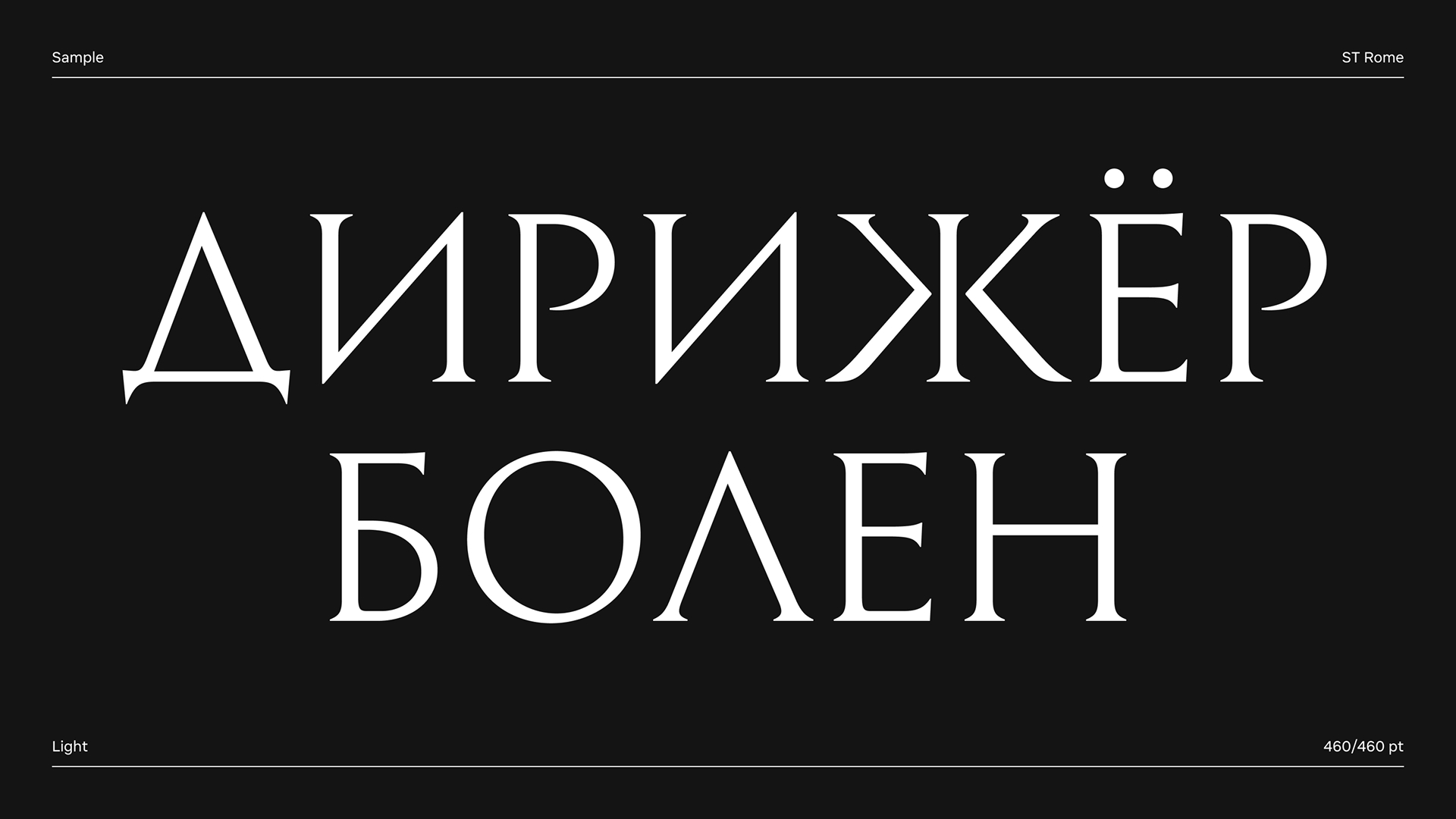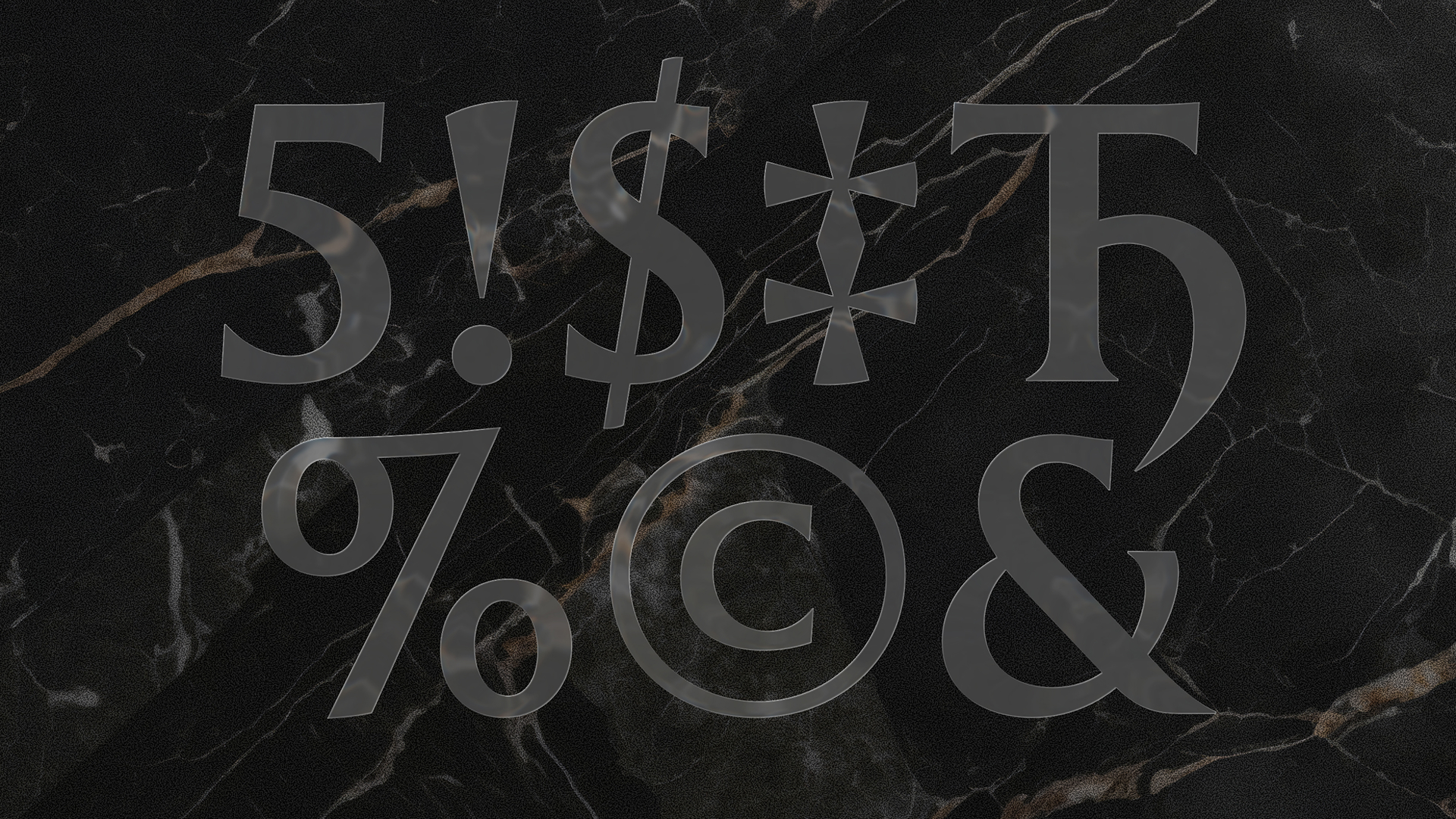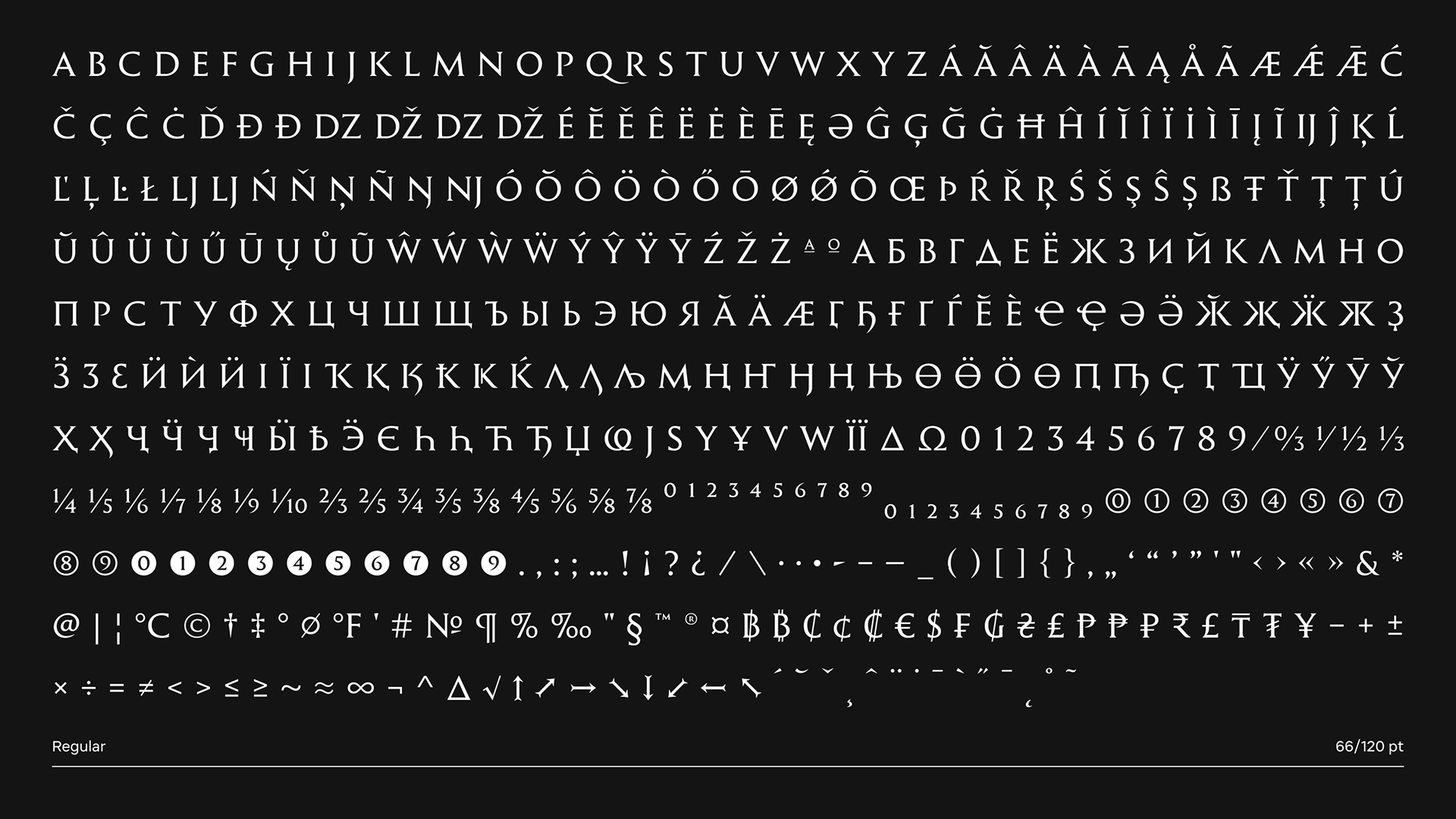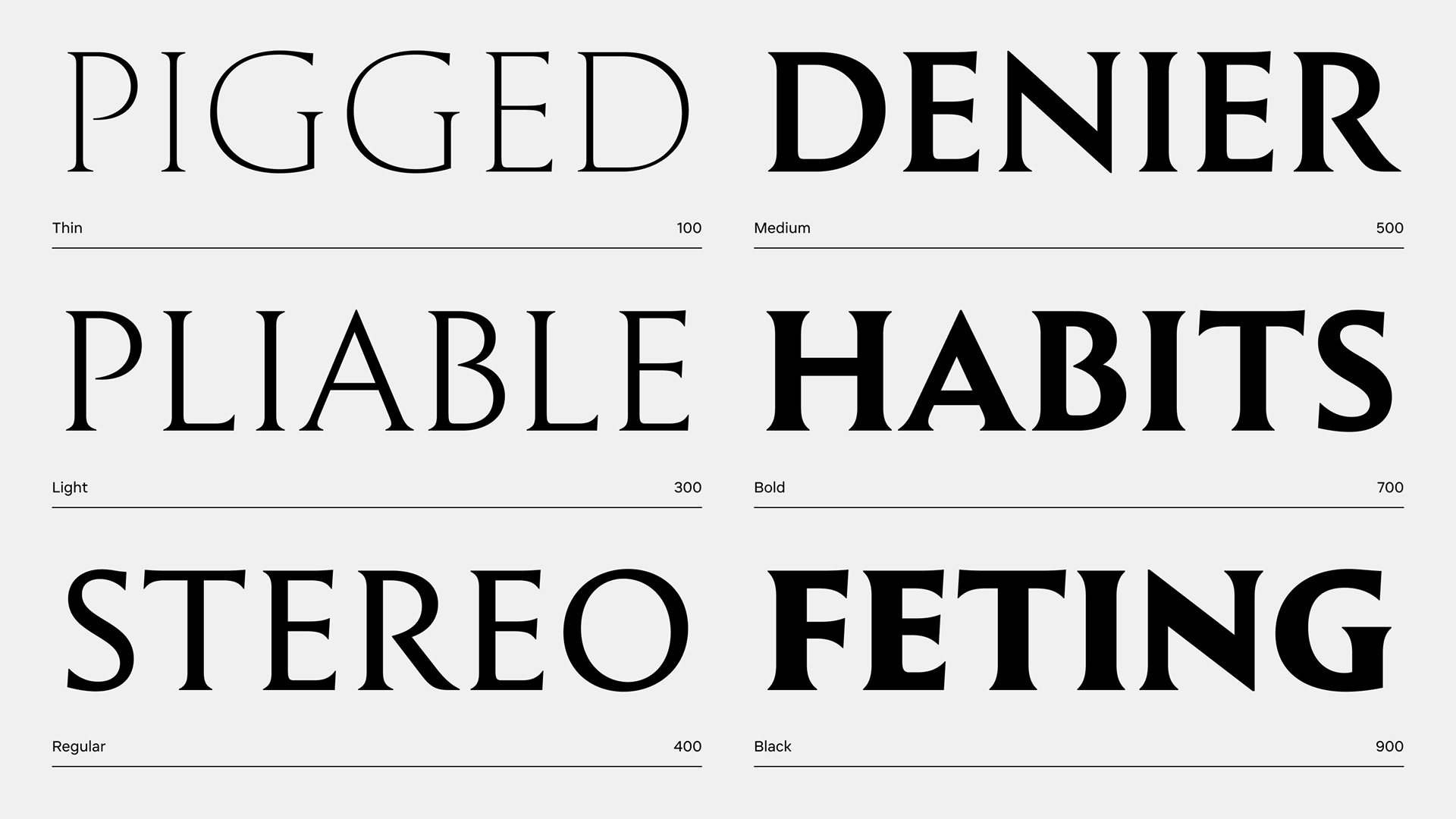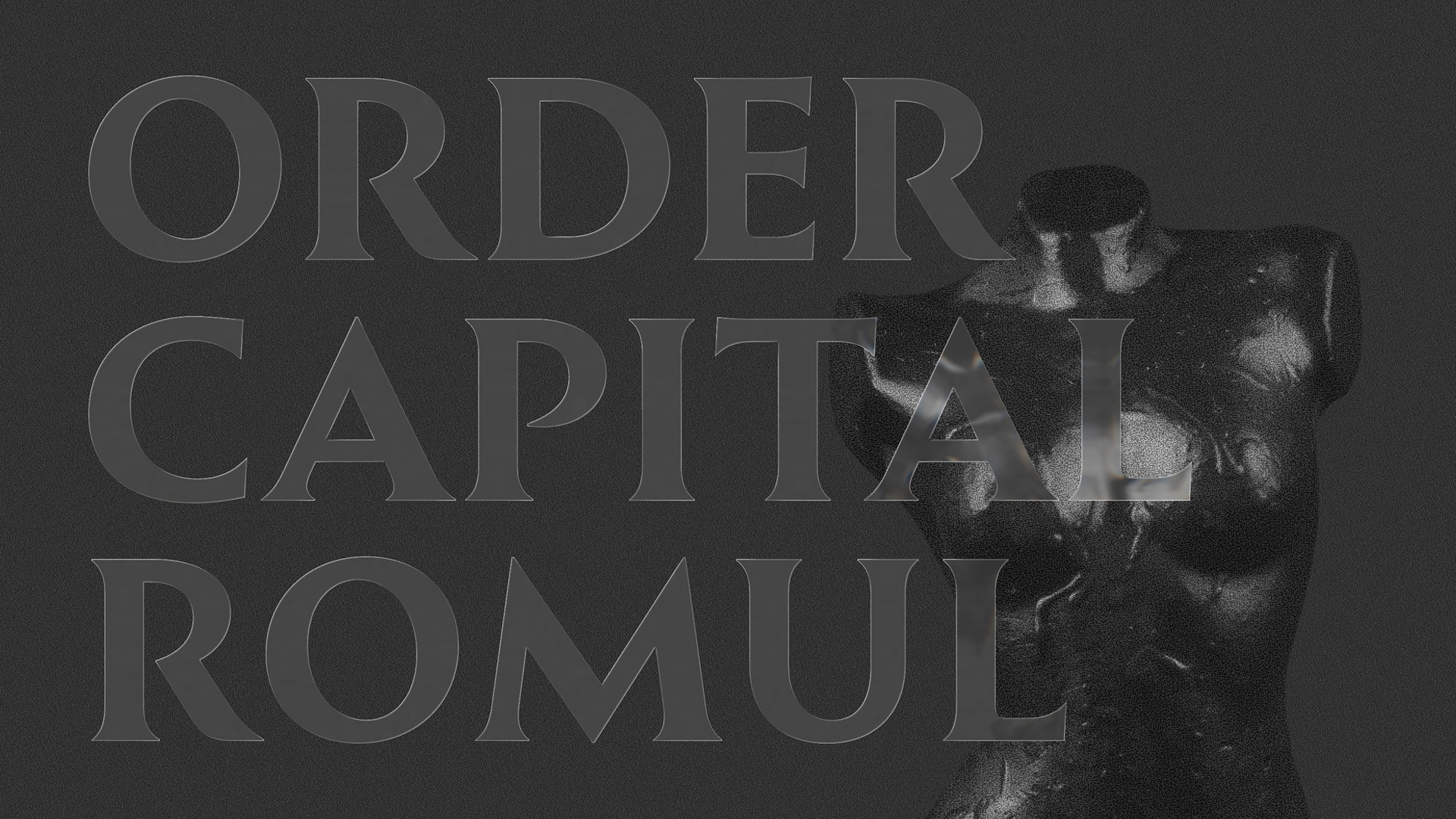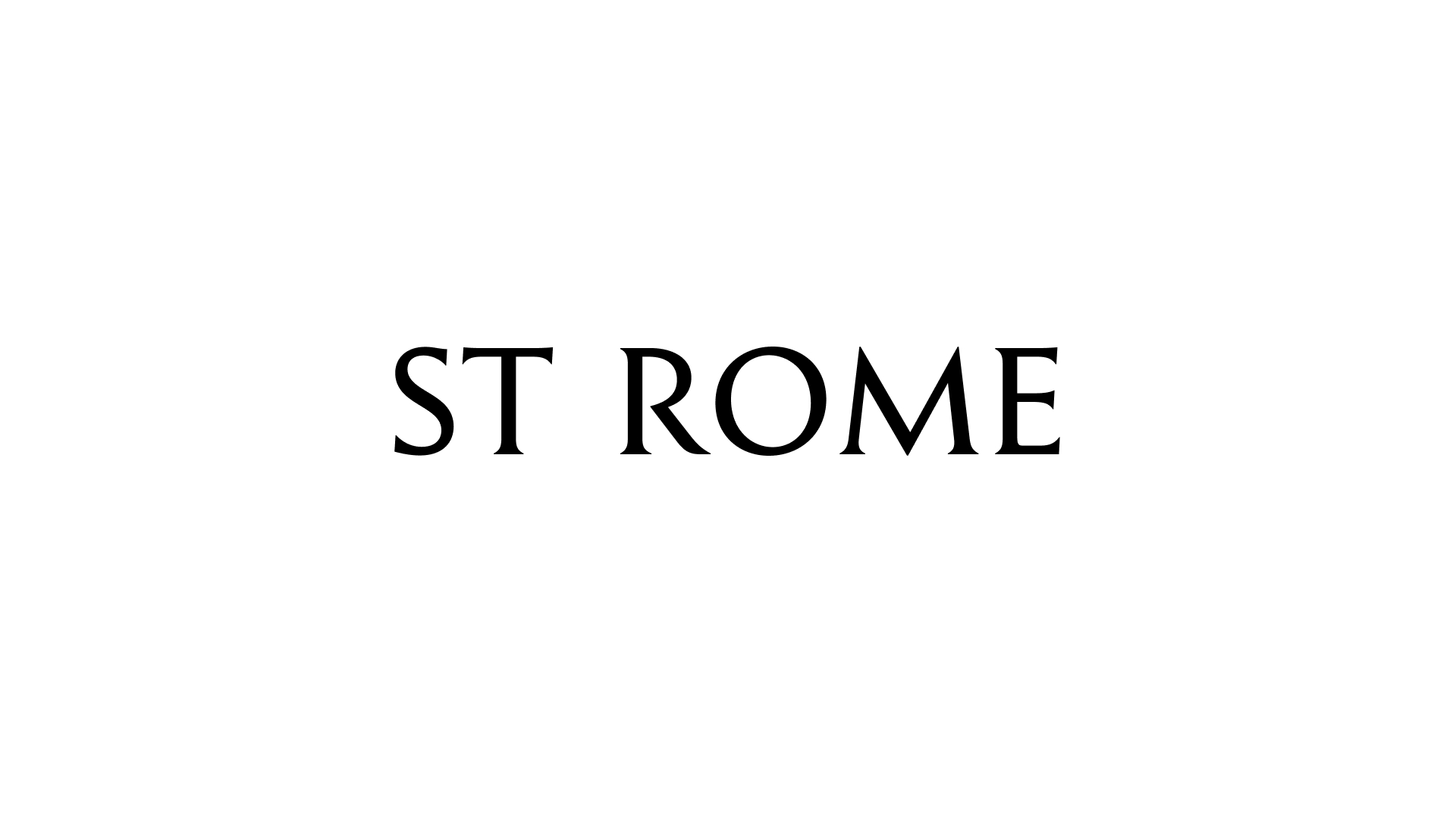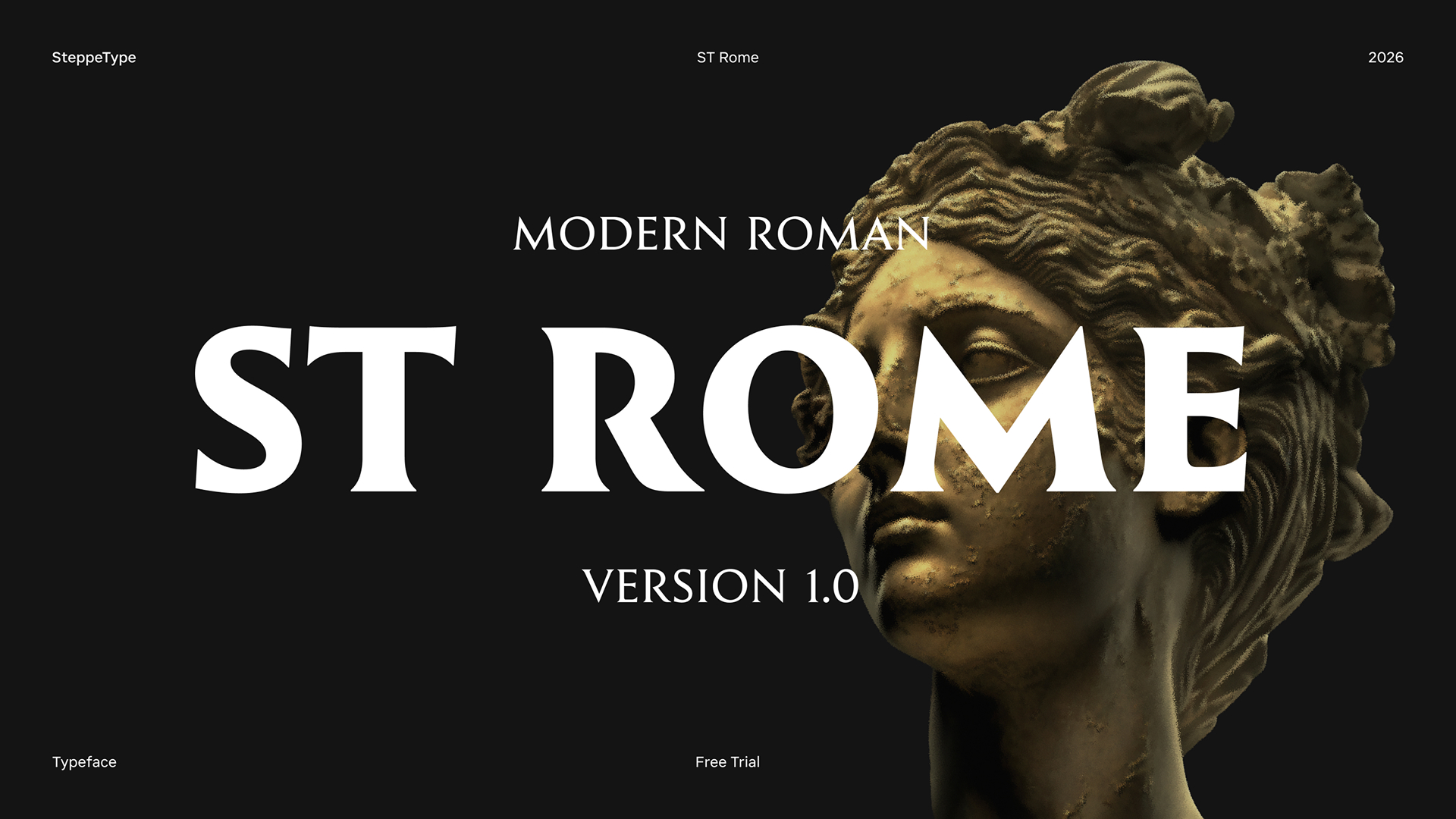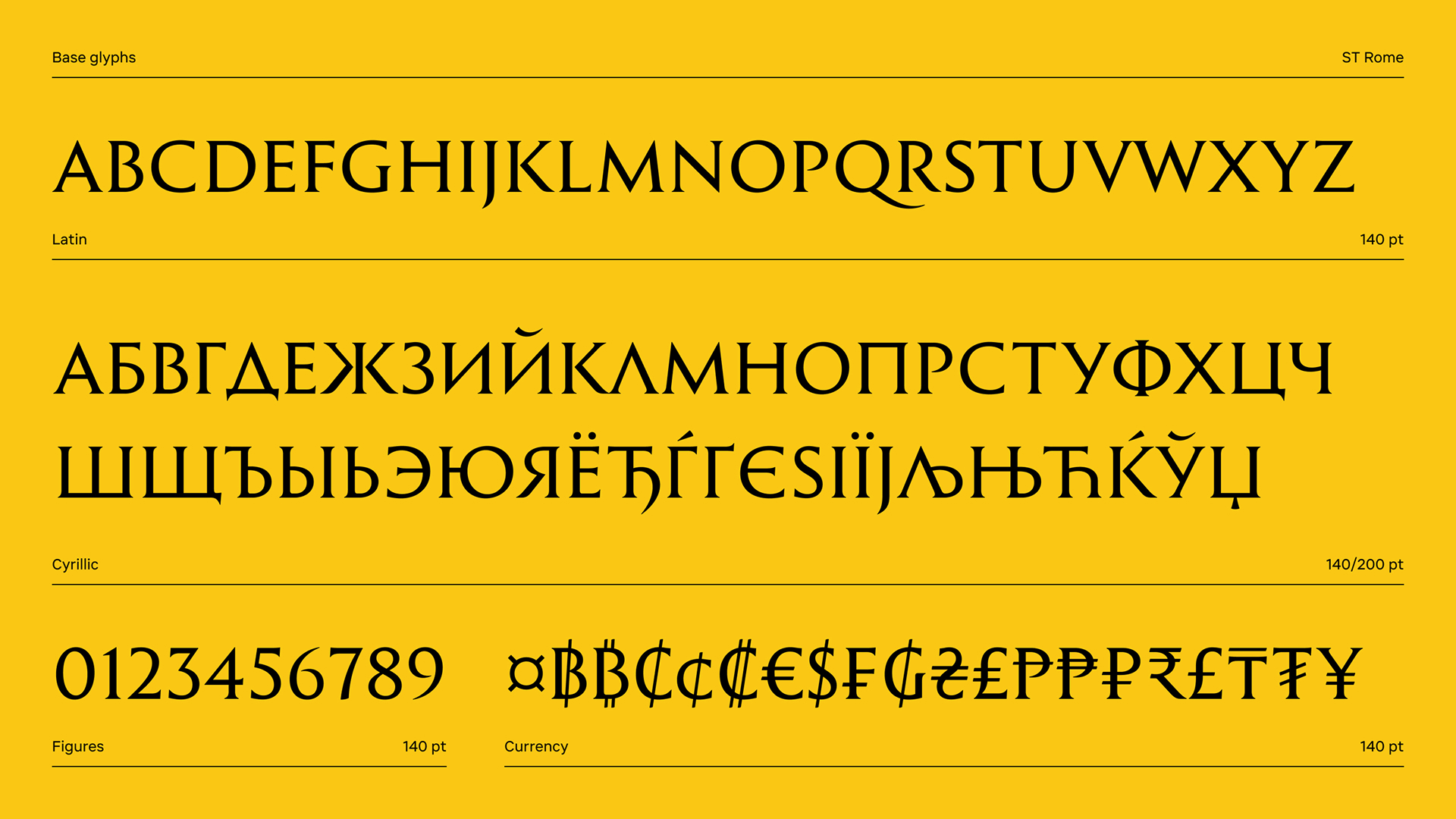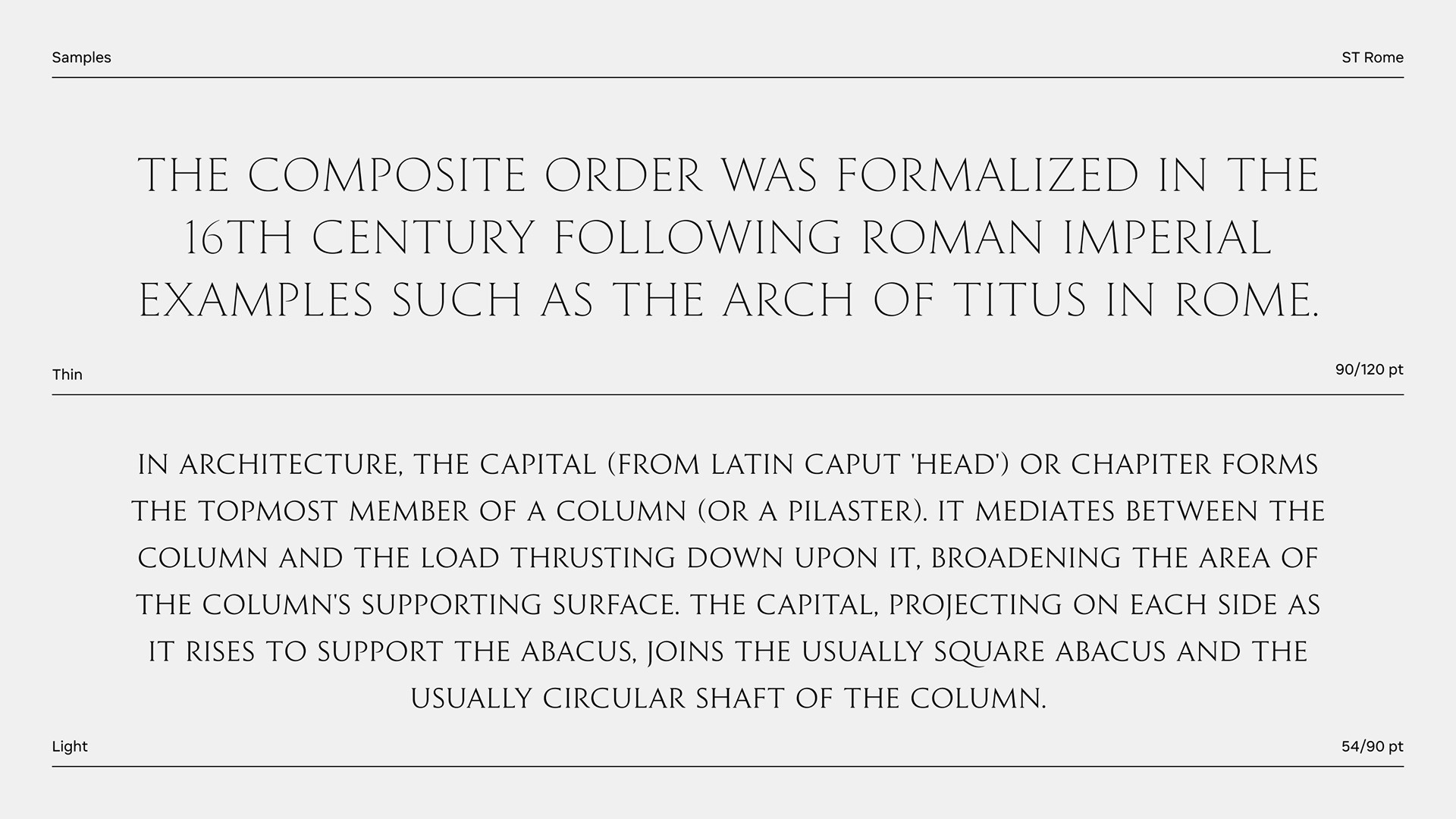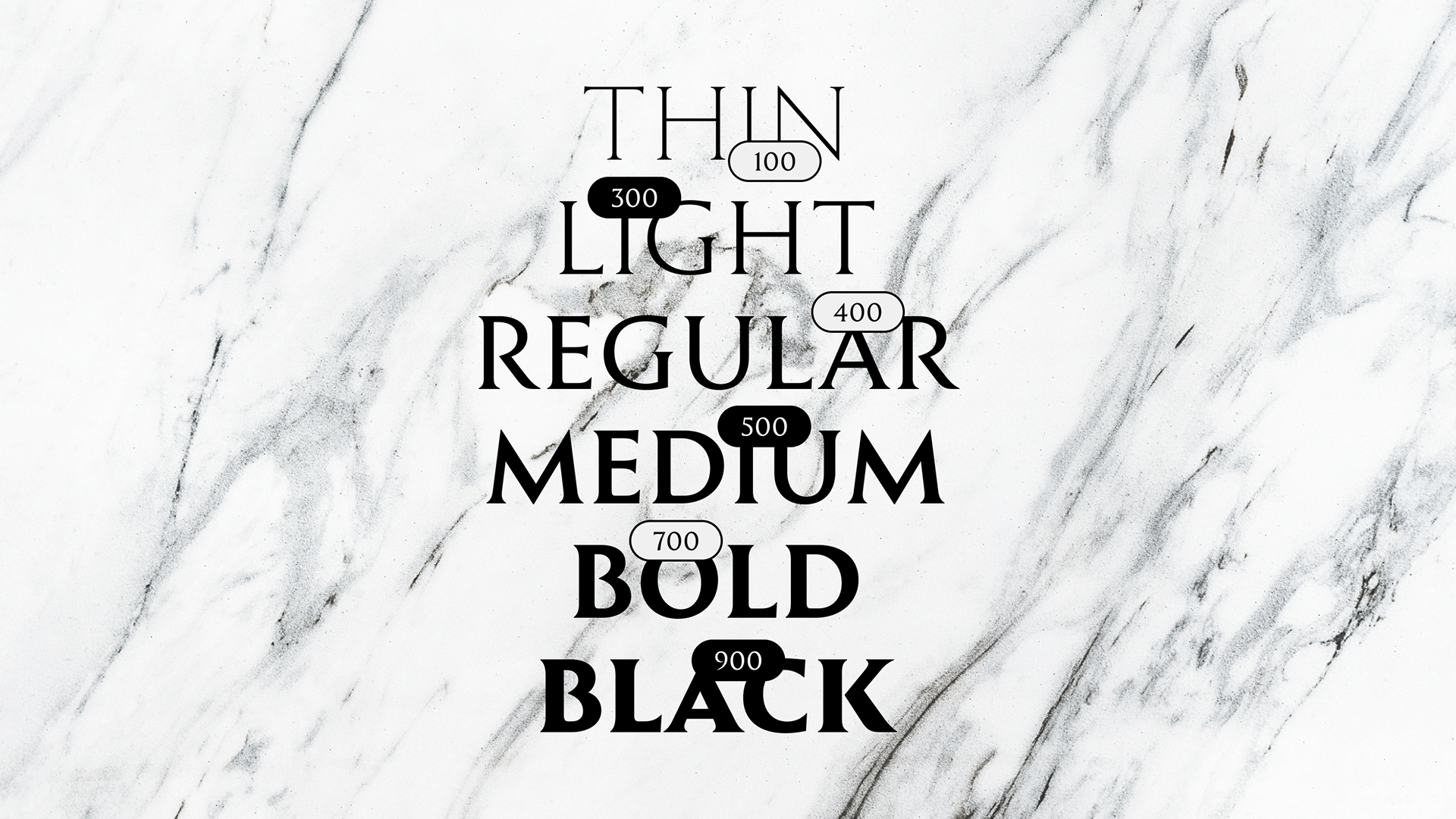
ST Rome
ST Rome — современная интерпретация римского капитального письма. Шрифт сохраняет характер ширококонечного пера, продолжает динамику оригинала. В то же время знаки очищаются от архаичности, увеличивая универсальность шрифтового инструмента. Контраст упрощён, формы основных конструкций и мелких деталей стали более геометричны. Шрифт раскрыт в 6 основных начертаниях с расширенной кириллицей и латиницей.
SteppeType
Игорь Степанченко
Игорь Степанченко, Шрифтовик